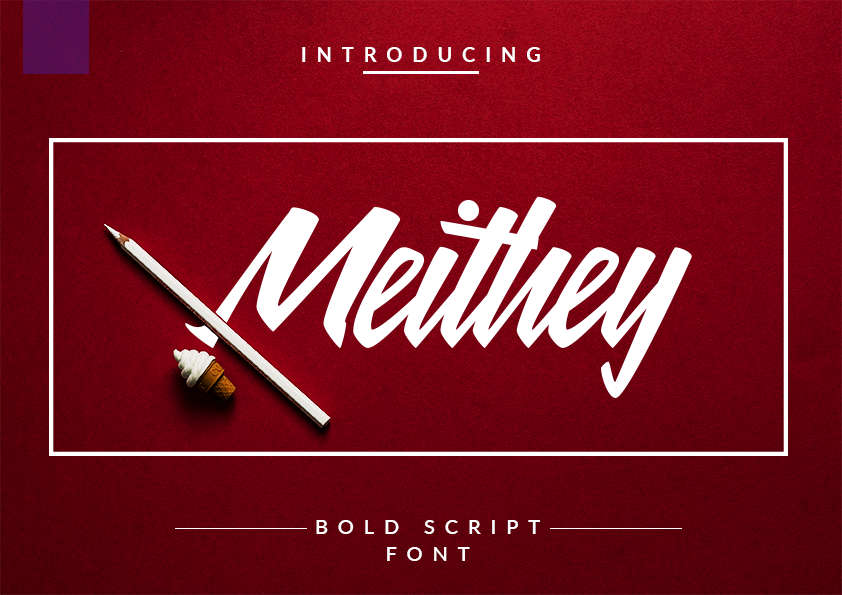
Olá amantes do design! Há tempos sonhava em encontrar uma fonte com esse charme elegante que retrata perfeitamente a arte da escrita tipográfica. Meithey Bold Script é um verdadeiro espetáculo para os olhos, projetada pela autora Wahyu Ichsan e agora disponível para todos nós na categoria de fontes serifadas. Esta moderna fonte oferece mais características do que você poderia imaginar, embora seja feita com amor. Meithey é uma fonte perfeitamente adaptável a várias aplicações, desde t-shirts e logotipos até marcas de produtos impressos ou mesmo em projetos digitais. Este tipo especializado vai trazer um toque único aos seus designs, transformando-os em verdadeiras obras de arte. Se você está procurando uma fonte que exalte a elegância da escrita calligráfica e que pode ser usada para criar uma variedade impressionante de resultados, Meithey Bold Script é definitivamente uma escolha inteligente. Não perca tempo, insira Meithey na sua próxima criação e surpreenda seus clientes!